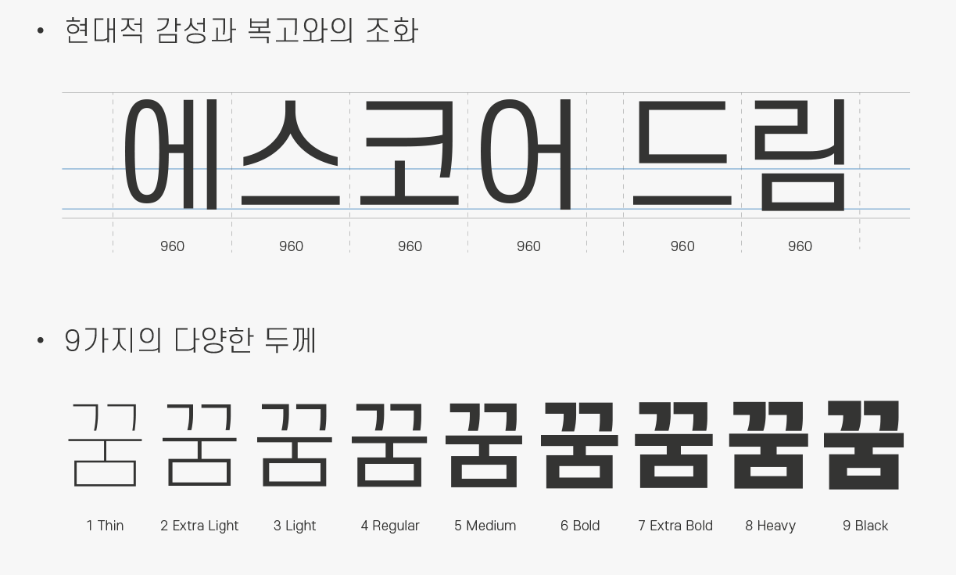
1. 기본 정보
| 항목 | 내용 |
|---|---|
| 폰트명 | 에스코어드림 (S-Core Dream) |
| 제작사 | S-Core |
| 굵기 | 9종 (Thin~Black) |
| 특징 | 직선적이면서도 세련된 디자인, 본문·제목 모두 활용 가능 |
3. 에스코어드림 특징
- 디자인 특성: 직선적인 균형감과 각진 형태로 정돈된 느낌 제공
- 가독성 우수: 본문, 소제목, 제목까지 다양한 용도에 활용 가능
- 굵기 다양성: 9단계 굵기 지원으로 디자인 자유도 확보
4. 활용 사례
- 출판물 제작: 워크북, 행사 책자, 교재 등에 적용 시 전문적인 느낌
- 디자인 작업: 웹사이트, 포스터, 브로슈어 제작 시 세련된 인상 제공
- 프레젠테이션: 제목과 본문에 모두 적용 가능해 균형감 있는 결과물 구현
5. 사용 팁
- 굵기 조절: 제목에는 BoldBlack, 본문에는 RegularLight 활용 추천
- 조합 활용: 같은 서체 내 굵기 조합만으로도 통일감 있는 디자인 가능
👉 가볍게 쓰기에도 좋고, 전문적인 디자인에도 어울리는 “만능 무료 서체”입니다.